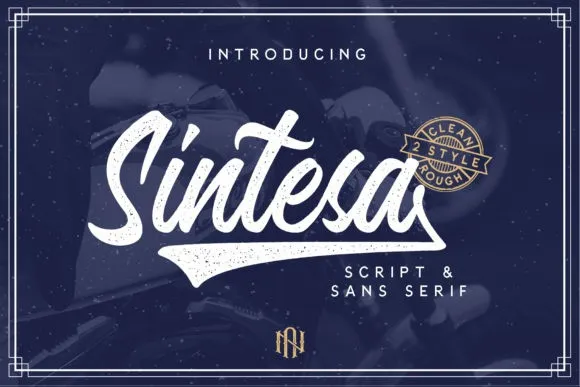
Sintesa Font Duo – Fonte Grátis
Sintesa Font Duo
A fonte Sintesa Font Duo é uma combinação envolvente de letra cursiva e sans-serif que oferece tanto estilo quanto funcionalidade. Ela apresenta belas ligaturas e alternativas para dar um toque elegante e único a qualquer projeto. As duas fontes contêm diversos alternativos contextualizados, formas inicial e terminal, além de ligações sofisticadas. O Sintesa Script é uma fonte única e poderosa que incorpora belos desenhos flutuantes, enquanto o Sintesa Sans continua o estilo elegante sem perder a modernidade. Esse duplo conjunto de letras perfeito para aqueles projetos que precisam de um toque retrô, como marcas d’água em fotografia ou logotipos e identidades visuais. É também ótimo para uso em invitations, anúncios, designs de produtos, rascunhos de ferramentas, design de casamentos, etiquetas e embalagens, eventos especiais — qualquer projeto que precise de um sabor autêntico da escrita à mão, misturado com a simplicidade do sans-serif. Sintesa Font Duo é uma escolha perfeita para quem procura tanto estilo quanto flexibilidade em suas fontes gráficas.